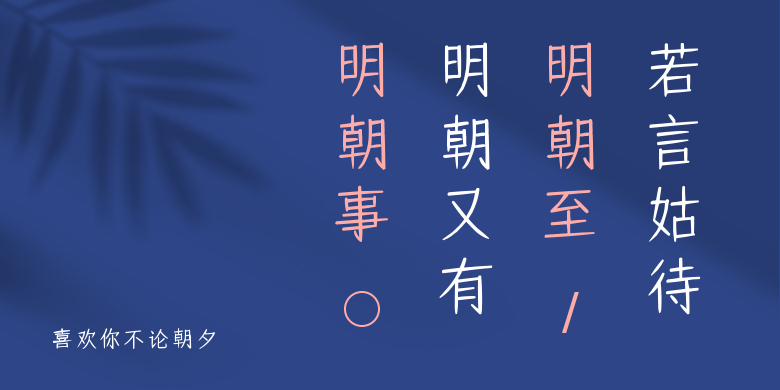
喜欢你不论朝夕
喜欢你不论朝夕,这款字体结构工整、笔画清晰,兼顾美观与易读性,适用于标题、正文、海报、包装、LOGO 等多种场景。字形优雅稳定,风格百搭耐看,适配日常排版与创意设计,让文字呈现更舒适、更具质感。喜欢你不论朝夕一笔一画,皆是细节,以均衡的比例、流畅的线条打造舒适视觉体验,字形端正大气,风格简约现代。无论是商业设计、品牌宣传还是日常排版,都能轻松驾驭,让文字更有格调与力量。喜欢你不论朝夕字体下载。